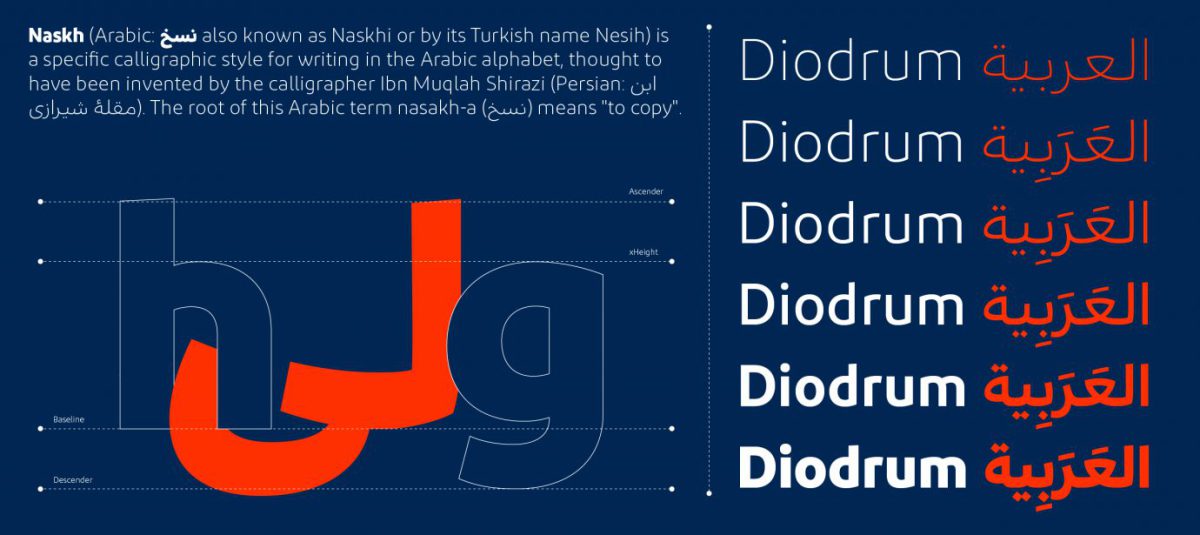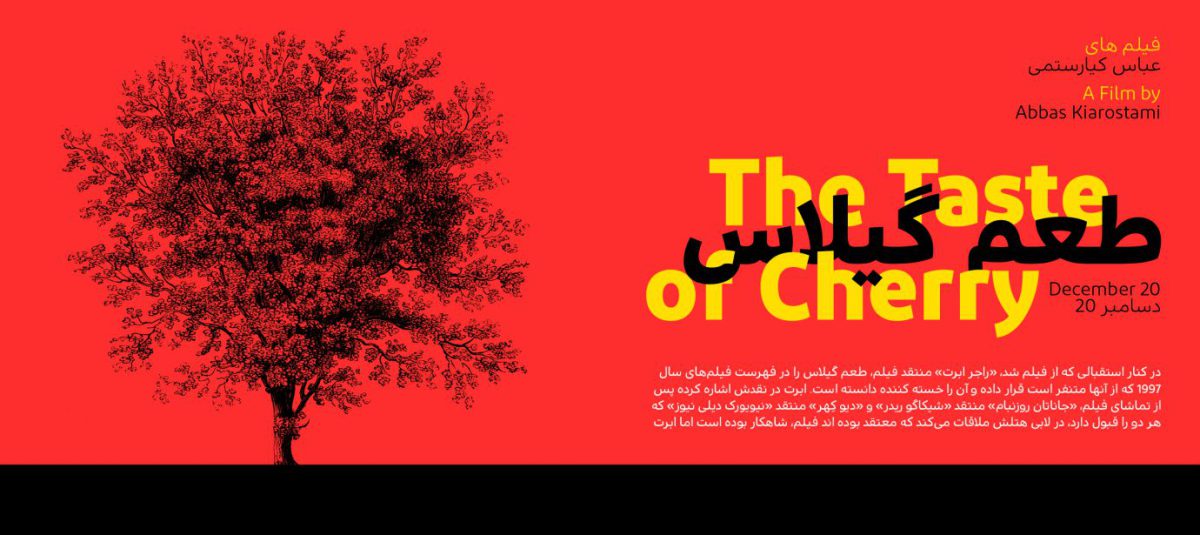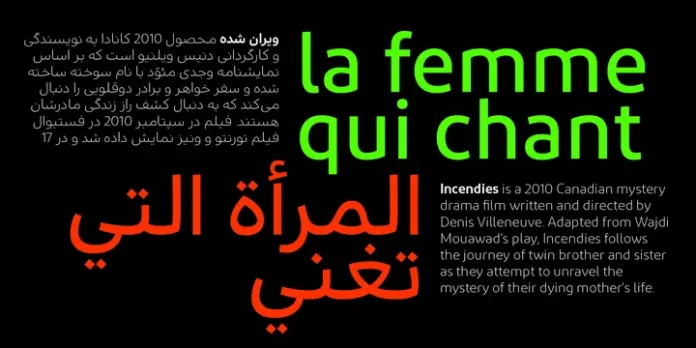
6 فونت دیودروم عربیک فارسی
فونت دیودروم عربیک یک تایپ فیس بسیار زیبا و حرفه ای است که در شش وزن مختلف طراحی و به صورت کاملاً رایگان منتشر شده است. این قلم تمامی حروف فارسی و انگلیسی را پشتیبانی می کند، که آن را برای انواع پروژه های طراحی گرافیکی و تولید محتوا بسیار مناسب می سازد. به دلیل طراحی کم کنتراست و ساختار مونو لاینر، دیودروم عربیک برای رابط کاربری (UI/UX) وب سایت ها و اپلیکیشن ها نیز ایده آل است و به دلیل تنوع وزن ها، انعطاف پذیری بالایی را برای طراحان فراهم می کند.
فونت دیودروم عربیک فارسی (۶ وزن): قلمی رایگان و حرفه ای برای طراحی
فونت دیودروم عربیک (Diodrum Arabic Font)، یک فونت عربی با پشتیبانی کامل از حروف فارسی و انگلیسی است که در شش وزن مختلف طراحی و منتشر شده است. این مجموعه فونت توسط بهمن اسلامی طراحی شده و به دلیل رایگان بودن، جایگزینی عالی برای فونت های تجاری مانند ایران یکان و ایران سنس به شمار می رود.
وزن های موجود در این خانواده فونت شامل اکسترا لایت (Extralight)، لایت (Light)، مدیوم (Medium)، رگولار (Regular)، سمی بولد (Semi Bold) و بولد (Bold) است. این تنوع وزن به طراحان امکان می دهد تا سلسله مراتب بصری را به خوبی ایجاد کرده و متن را متناسب با نیازهای مختلف طراحی، تنظیم کنند.
دیودروم عربیک با طراحی کم کنتراست به سبک نسخ (Naskh)، تأکید ویژه ای بر افقی بودن حروف دارد. این ویژگی از طریق کنترفورم های بزرگ و باز و همچنین برجسته سازی بخش های میانی حروف به دست آمده است. این طراحی به ویژه برای پروژه های هویت شرکتی، طراحی سرمقاله و پروژه های UI/UX بهینه شده است. همچنین، بسیاری از خطوط شروع یا پایان حروف و نقاط و علائم خط عربی، دارای زاویه های ظریفی هستند که حسی از کالیگرافی را به این فونت سنس سریف (sans serif) بازمی گردانند.
کاربردها: توسعه بصری در پلتفرم های مختلف
فونت دیودروم عربیک با شش وزن و پشتیبانی از هر دو زبان فارسی و انگلیسی، برای طیف وسیعی از کاربردها در محیط های چاپی و دیجیتال مناسب است:
- طراحی گرافیکی و تبلیغات: ایده آل برای طراحی جلد کتاب، بیلبوردهای شهری، تراکت، کارت ویزیت، و کاورهای اینستاگرامی.
- تولید محتوا و نشر: مناسب برای وب سایت ها، وبلاگ ها، محتوای آنلاین، مجلات، روزنامه ها و گزارش ها به دلیل خوانایی بالا و ظاهر مدرن.
- طراحی رابط کاربری (UI/UX): به دلیل داشتن وزن های متفاوت و طراحی بهینه، این فونت برای طراحی رابط کاربری وب سایت ها و اپلیکیشن ها بسیار کاربردی است و به عنوان یک فونت حرفه ای به زیبایی و کارایی طراحی شما می افزاید.
- برندینگ و هویت بصری: مناسب برای طراحی لوگو و سایر عناصر برندینگ که نیاز به یک فونت با ظاهر حرفه ای و مدرن دارند.